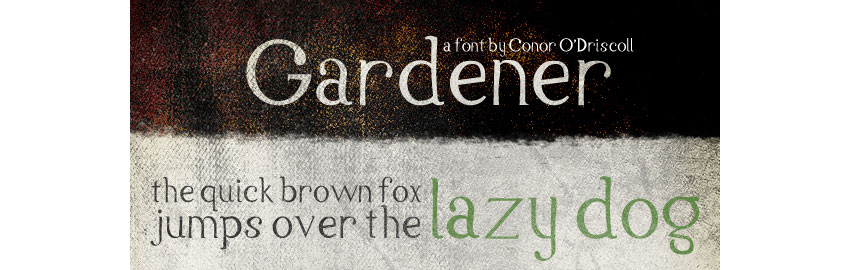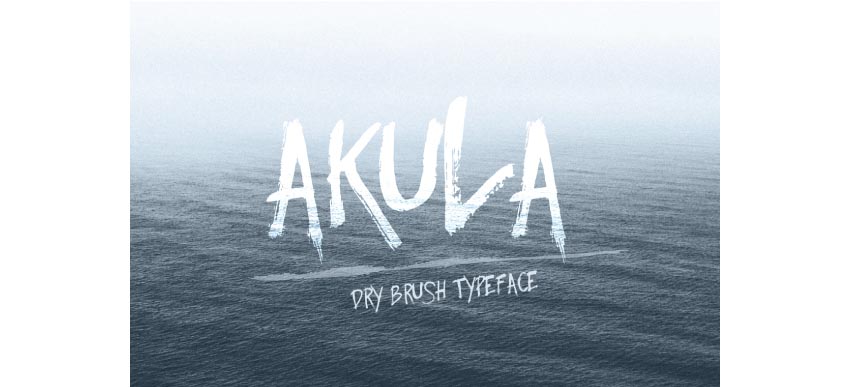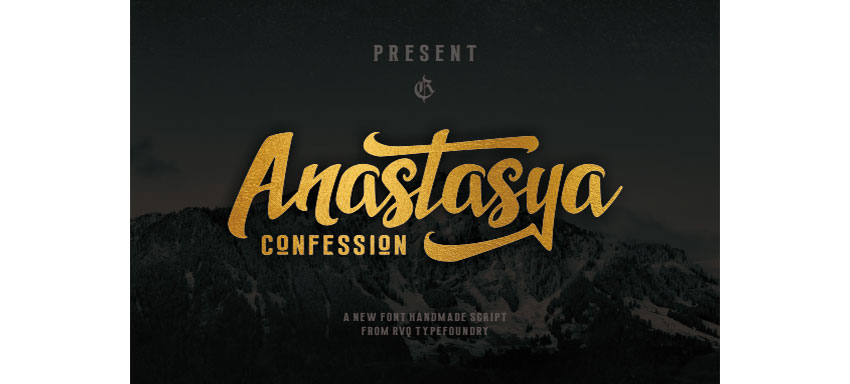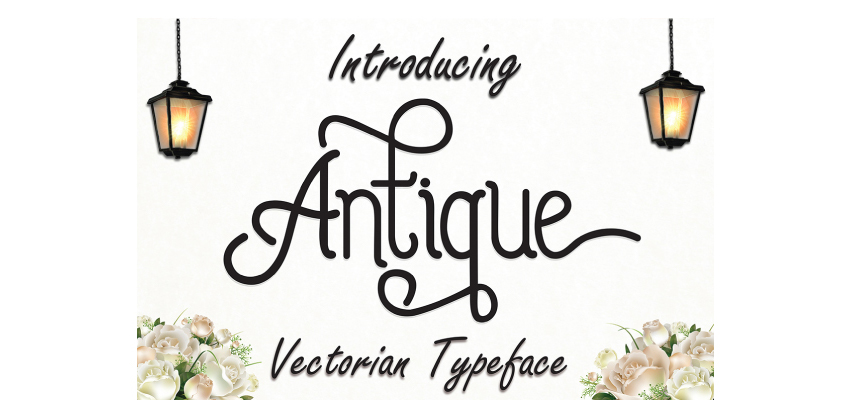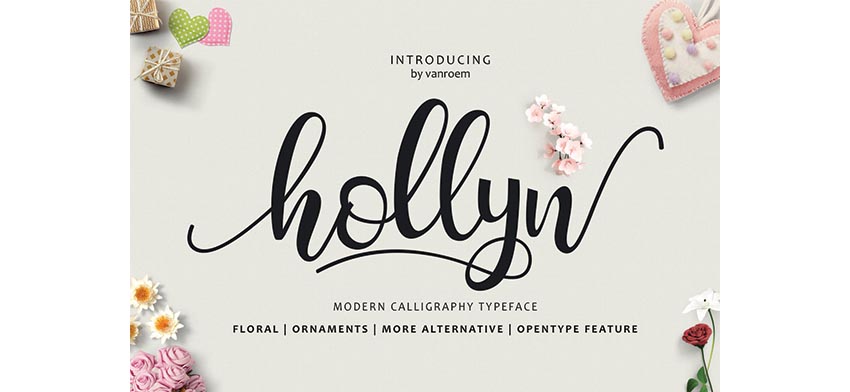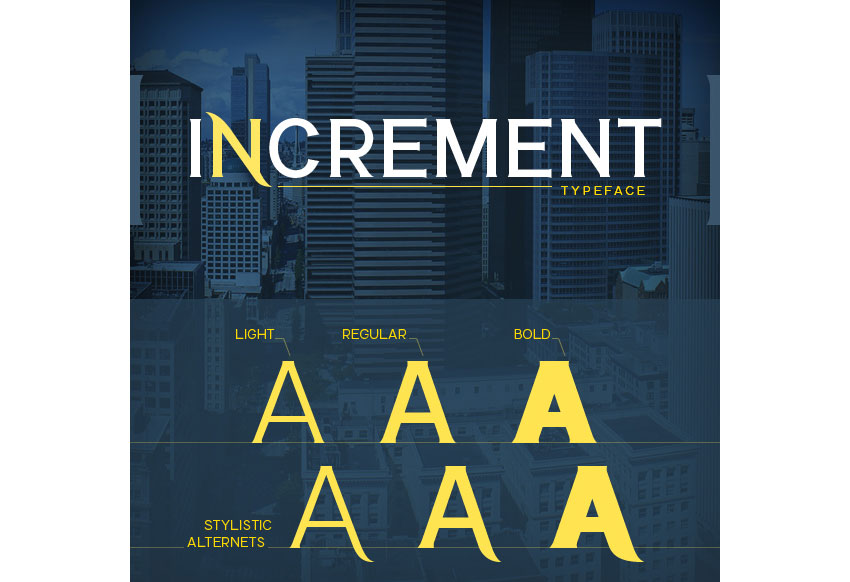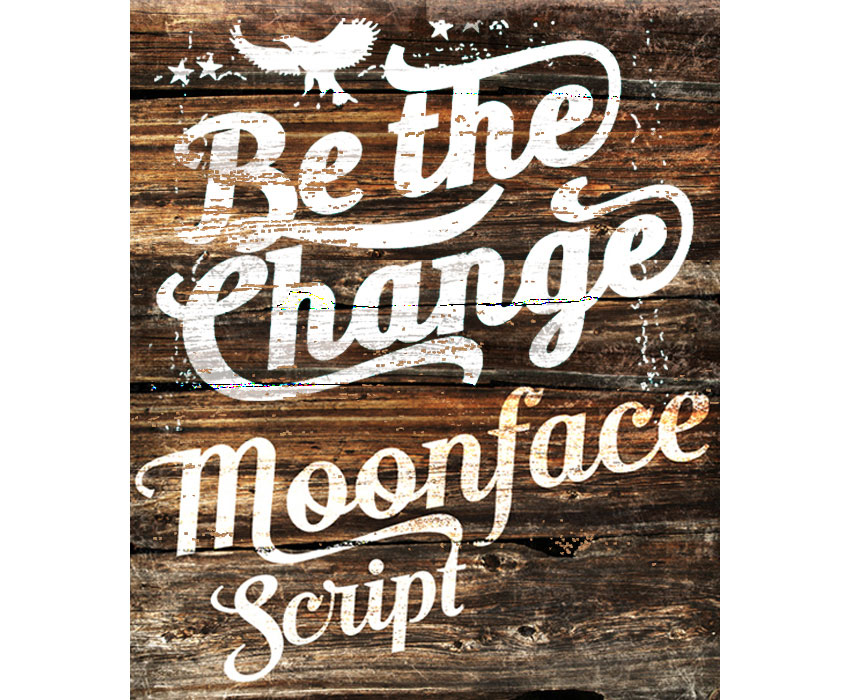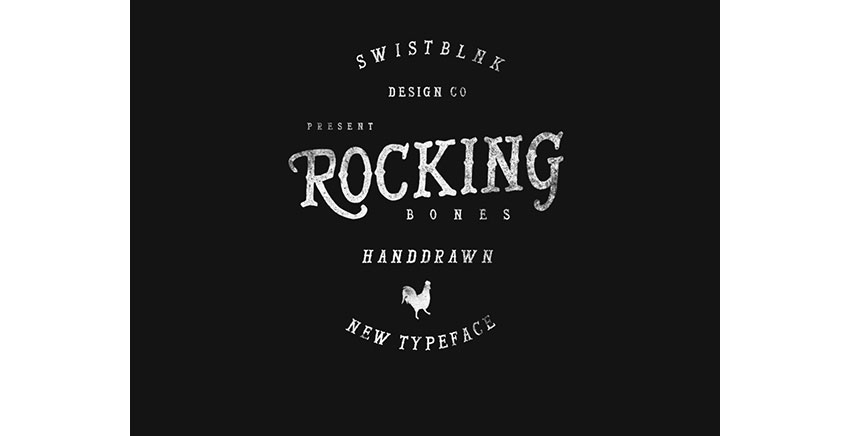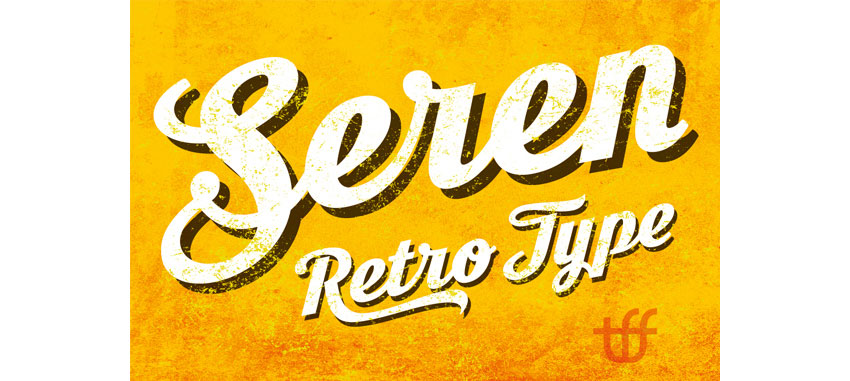
Những Font chữ đẹp các nhà thiết kế đồ họa cần phải có
Để tránh sự nhàm chán khi thiết kế với những Font chữ truyền thống, các designer thường sử dụng những Font chữ đẹp giúp tác phẩm thêm phần sáng tạo, chuyên nghiệp. Trong bài viết này chúng tôi xin gợi ý cho bạn những Font chữ đẹp đang hot nhất hiện nay để bạn tham khảo.
1.Vài nét về Font chữ đẹp
Font chữ đẹp là bộ sưu tập nhiều font chữ đẹp nhất nhằm phục vụ cho công việc thiết kế đồ họa hay nhiều mục đích tương tự. Đối với các design thì những Font chữ đẹp như một thành phần không thể thiếu hỗ trợ cho công việc sáng tạo của mình. Cùng với sự phát triển của công nghệ, càng ngày càng có thêm nhiều font chữ đẹp và độc đáo cho bạn thỏa sức lựa chọn.
Nhiều Font chữ đã được việt hóa để bạn có thể tạo các văn bản hay file đồ họa bằng tiếng Việt. Với các font chữ đẹp này,  người dùng có thể tạo ra các loại poster, áp phích, các loại slogan... để phục vụ cho nhiều mục đích  khác nhau.
2. Tổng hợp các font chữ đẹp nhất
Chúng tôi đã tổng hợp từ nhiều nguồn tin khác nhau để gửi đến bạn những Font chữ đẹp đang được ưa chuộng nhất hiện nay như:
2.1. Gardener Font
Font chữ này là kiểu kết hợp bởi kết cấu tự nhiên với độ cứng trong kiểu serif, nó thường được dùng để thêm tạo điểm nhấn trên homemade vào thiết kế bao bì hoặc những tác phẩm in ấn cần cảm giác hữu cơ và nuôi trồng tại nhà.
2.2. Typewriter
Khi bạn cần một kiểu máy đánh chữ cổ cho thiết kế của bạn thì kiểu Font chữ Typewriter chính là sự lựa chọn tuyệt vời. Người dùng thường yêu thích cách thể hiện chi tiết trong các mẫu chữ không đồng nhất mà một chiếc máy đánh chữ thực sự có thể tạo ra.
2.3. Increment Font
Phông chữ này mang hai bộ phong cách đó là: một chút kiểu serif và loại có các nét cong ấn tượng. Chúng được trộn lẫn với nhau một cách tuyệt vời đề tạo nên một văn bản với diện mạo và kiểu cách, ấn tượng.
2.4. Rocking Bones
Phông chữ serif theo phong cách vintage quả là sự lựa chọn tuyệt vời cho các logo và thiết kế in ấn. Với phong cách in tay xen kẽ và điểm thêm một số vectơ, phông chữ này cung cấp cho người dùng mọi thứ để tạo ra một số thiết kế cổ điển ấn tượng.
2.5. Violina Typeface
Font chữ serif này tạo cho người nhìn một cảm giác retro ngộ nghĩnh trong khi vẫn giữ được phong cách sành điệu. Với rất nhiều glyph để chọn lựa, Violina chắc chắn sẽ góp phần cho bản vẽ của bạn độc đáo hơn.
2.6. Anastasya Confession
Đây là một kiểu chữ viết script bằng cọ khá bóng bẩy mà các nhà thiết kế chuyên nghiệp khuyên bạn nên sử dụng cho thương hiệu, nội dung truyền thông xã hội và nhiều tác phẩm nghệ thuật quảng cáo nữa.
2.7. Moonface Script
Moonface Script mang phong cách theo kiểu bóng chày và thể thao phù hợp cho y phục và các công việc thiết kế khác, nó có một số hình dạng cái roi lớn nằm trong khuôn khổ dạng chữ của nó.
2.8. Akula- Dry Brush Font
Những font chữ dạng vẽ cọ khô được coi như một sự bổ sung tuyệt vời cho bộ sưu tập của người dùng chuyên dành cho các tài liệu tiếp thị và tác phẩm thiết kế in ấn. Akula là một ví dụ rất điển hình cho phong cách đó.
2.9. Seren Script
Font chữ retro in đậm này là một sự thay thế hoàn hảo cho một vài font chữ lấy cảm hứng retro thông dụng hơn, mà nó đã xuất hiện ở trên mọi tiêu đề blog trong một vài năm trước.
2.10. Hollyn Script + Extras Font
Phông chữ thư pháp hiện đại này chính  là một câu trả lời xúc tích phù hợp sử dụng trong các kiểu vẽ tay. Cho dù bạn đang muốn thiết kế về thương hiệu, truyền thông in ấn, hay các tài liệu tiếp thị với phông chữ thanh lịch thì Font chữ này cũng sẽ là sự lựa chọn thông minh để giữ công việc của bạn luôn tươi mới.
2.11. Burnts Marker Typeface
Font chữ này được tạo ra nhờ cảm hứng từ nghệ thuật đường phố, đây là một loại font chữ tuyệt đẹp mà không bao giờ bị mất đi cái nhìn thu hút của nó. Burnts Marker Typeface là một sự bổ sung tuyệt vời cho các bộ sưu tập của nhà thiết kế và tạo nội dung hấp dẫn cho công việc in ấn và thiết kế sản phẩm.
2.12. Antique Typeface
Antique là một font chữ rất thanh lịch tuyệt vời hoàn toàn đúng với cái tên của nó.